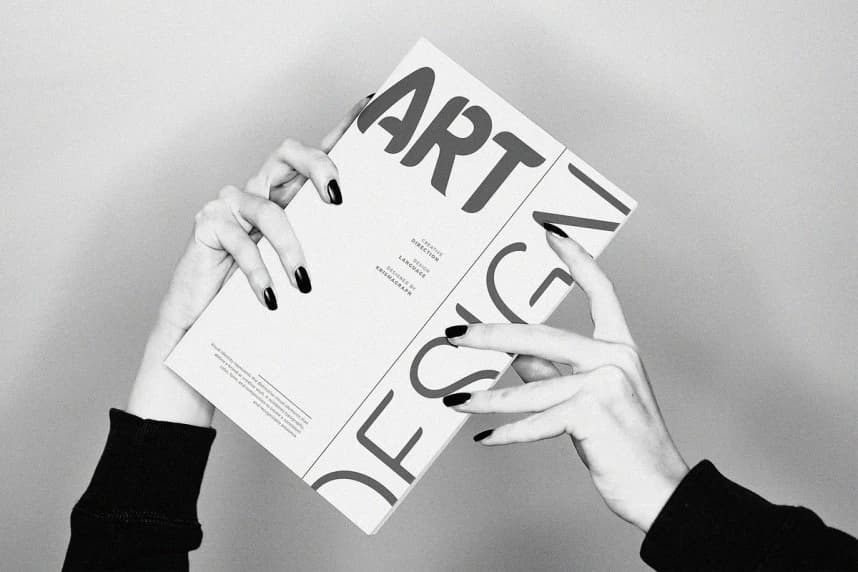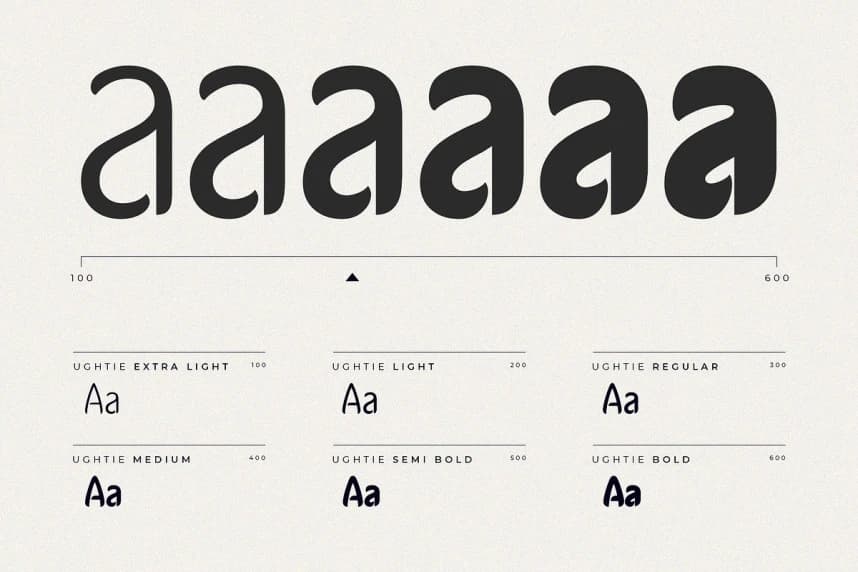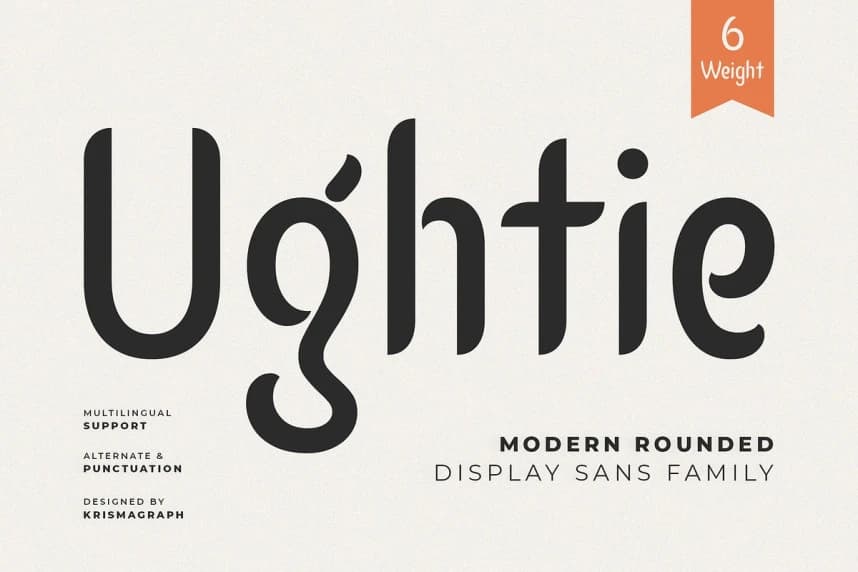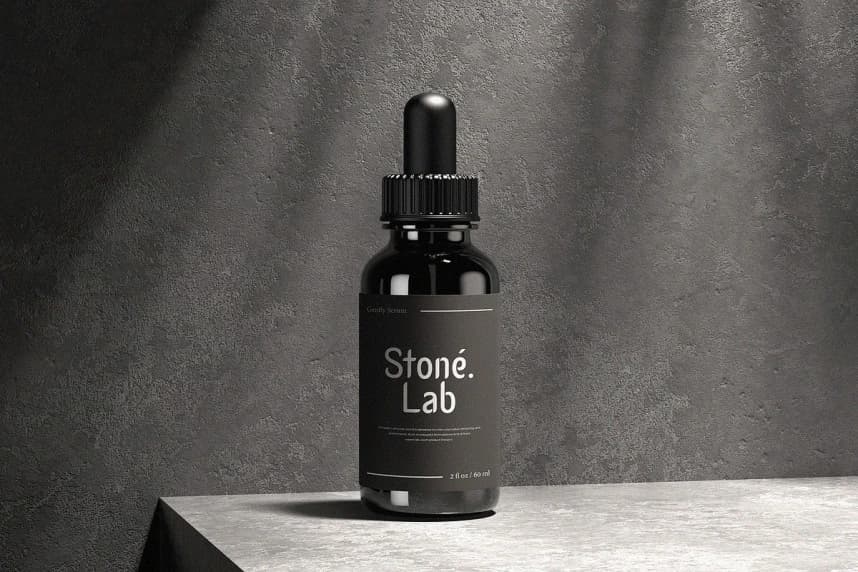
Ughtie Font, geometrik yapı ile sıcak yaklaşılabilirlik arasında zarif bir denge kuran çağdaş, yuvarlak hatlı bir gösterişli sans-serif ailesidir. Light'tan Extra Bold'a kadar 6 farklı ağırlıkla — karmaşık tasarım sistemleri için tipografik esneklik sunar, kişiliğini feda etmeden.
Ughtie Font, geometrik yapı ile sıcak yaklaşılabilirlik arasında zarif bir denge kuran çağdaş, yuvarlak hatlı bir ekran için tasarlanmış sans-serif ailesidir. 6 farklı ağırlıkla — hafiften ekstra kalına kadar — karmaşık tasarım sistemleri için tipografik esneklik sunar, kişiliğini kaybetmeden.